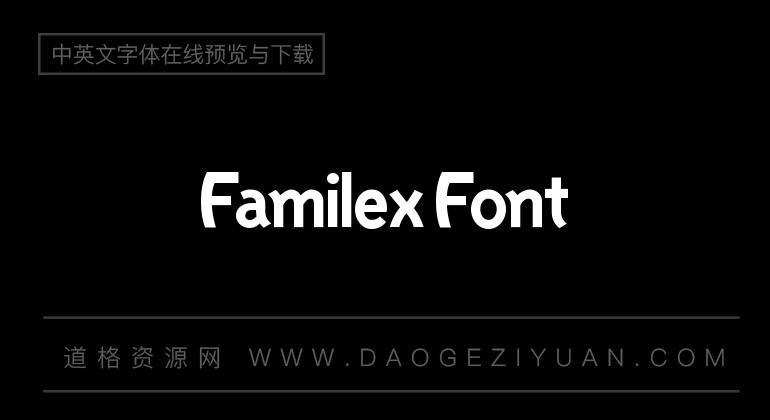
Familex Font是一种基于Latin文字符号的免费字体,适用于个人和商业用途。它的设计灵感来源于传统的印刷体,具有清晰、简洁、易读的特点。字体家族包括正常、斜体、粗体和粗斜体四个字重,每个字重都包含大写字母、小写字母、数字和标点符号等字符。此外,它还支持多种语言字符集,包括英语、西班牙语、德语、法语、意大利语、葡萄牙语等。Familex Font的自然线条和优美的比例使得它在许多场合下都能表现出色,如印刷品、海报、标志设计、网站设计等。内容介绍
Familex Font是一款非常不错的手写艺术字体,具有很好的视觉感,适合于文化类的宣传设计、商业类品牌的广告和产品包装设计以及个性化文字排版等较多场景。